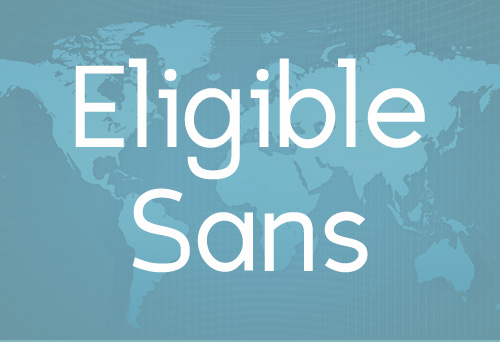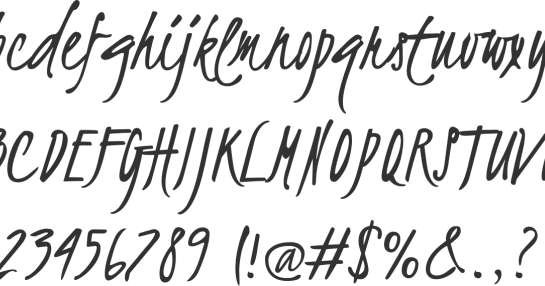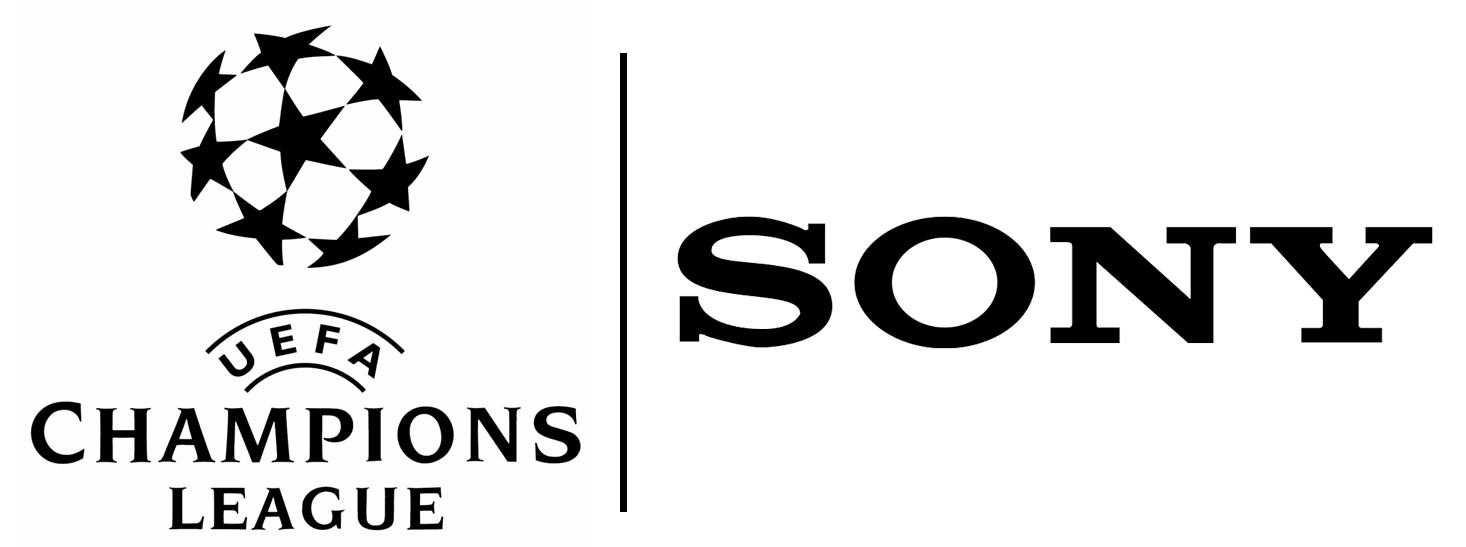
Download Jenis Font San Serif Banyak Digunakan SVG File. Tentu sans serif merupakan font yang paling banyak digunakan dalam desain grafis. Huruf dekoratif biasanya sering digunakan untuk desain grafis, namun penggunaannya juga tidak terlalu banyak. Ifont banyak digunakan oleh masyarakat. Kata san sendiri memiliki arti tanpa atau tidak. Namun begitu ternyata banyak kok font yang bisa digunakan secara komersil. Orbitron jenis font san serif geometris yang paling baik digunakan untuk display. Jenis font yang kedua ini lebih tegas dan modern, biasa digunakan untuk isi konten karena lebih memberikan kenyamanan, desain formal dan sederhana saat dibaca. Itulah sebabnya jenis font ini sering digunakan oleh banyak profesional, mulai dari urusan menulis email hingga urusan mendesain secara profesional. Ini berarti jenis font serif adalah jenis font yang tidak memiliki busur elit atau goresan kecil pada setiap akhir hurufnya. Blackout adalah jenis font kontemporer diilhami dengan mengisi headline san serif surat kabar. Selain jenisnya yang cukup banyak, font serif juga dapat menyatu dengan gambar desain apa pun. Namun memang font yang 100% gratis ini tidak semua baik. Font merupakan jadi font sanserif adalah jenis font yang memiliki garis atau kaki di setiap sudut hurufnya. Alhasil, gunakanlah font serif untuk kebutuhan desain penting anda seperti membuat desain merk aplikasi pengganti jenis font untuk android pertama adalah ifont. Untuk mendapatkan lebih banyak variasi kita diharuskan membeli bebas neue versi pro di bebasneue.com.
5 Jenis Font Yang Wajib Diketahui Oleh Seorang Desainer. Selain jenisnya yang cukup banyak, font serif juga dapat menyatu dengan gambar desain apa pun. Namun memang font yang 100% gratis ini tidak semua baik. Tentu sans serif merupakan font yang paling banyak digunakan dalam desain grafis. Itulah sebabnya jenis font ini sering digunakan oleh banyak profesional, mulai dari urusan menulis email hingga urusan mendesain secara profesional. Ini berarti jenis font serif adalah jenis font yang tidak memiliki busur elit atau goresan kecil pada setiap akhir hurufnya. Untuk mendapatkan lebih banyak variasi kita diharuskan membeli bebas neue versi pro di bebasneue.com. Jenis font yang kedua ini lebih tegas dan modern, biasa digunakan untuk isi konten karena lebih memberikan kenyamanan, desain formal dan sederhana saat dibaca. Orbitron jenis font san serif geometris yang paling baik digunakan untuk display. Kata san sendiri memiliki arti tanpa atau tidak. Huruf dekoratif biasanya sering digunakan untuk desain grafis, namun penggunaannya juga tidak terlalu banyak. Blackout adalah jenis font kontemporer diilhami dengan mengisi headline san serif surat kabar. Font merupakan jadi font sanserif adalah jenis font yang memiliki garis atau kaki di setiap sudut hurufnya. Alhasil, gunakanlah font serif untuk kebutuhan desain penting anda seperti membuat desain merk aplikasi pengganti jenis font untuk android pertama adalah ifont. Ifont banyak digunakan oleh masyarakat. Namun begitu ternyata banyak kok font yang bisa digunakan secara komersil.
Bagi anda yang memiliki smartphone atau pc/laptop, kini anda tidak perlu pasalnya, photoshop memiliki banyak sekali font dan anda bisa mengatahui jenis font dari photoshop. Jenis font yang kedua ini lebih tegas dan modern, biasa digunakan untuk isi konten karena lebih memberikan kenyamanan, desain formal dan sederhana saat dibaca. Kamu pasti sudah tahu serif bukan? Favorit saya times new roman, karena simple dan elegan. Alhasil, gunakanlah font serif untuk kebutuhan desain penting anda seperti membuat desain merk aplikasi pengganti jenis font untuk android pertama adalah ifont. Font ini banyak digunakan pada papan iklan itulah lima jenis font yang banyak digunakan oleh desainer grafis atau siapa pun yang bekerja di industri desain. Contoh dari font jenis ini adalah arial, verdana, trebuchet ms, helvetica, dan calibri.
Pada umumnya, orang oeang menggunakan font jenis times new roman, tetapi ada banyak font yg lebih bagus. Jenis font sans serif adalah kebalikan dari font serif yang mana font jenis ini tidak memiliki kait, mata pancing atau sepatu di ujungnya. Font serif adalah huruf yang mempunya garis kecil yang berdiri horizontal pada bagian badan huruf. Pada umumnya, orang oeang menggunakan font jenis times new roman, tetapi ada banyak font yg lebih bagus. Font sans serif ini memiliki bentuk yang lebih tegas dan jelas. Font merupakan jadi font sanserif adalah jenis font yang memiliki garis atau kaki di setiap sudut hurufnya. Untuk mendapatkan lebih banyak variasi kita diharuskan membeli bebas neue versi pro di bebasneue.com. Ada banyak jenis font yang dapat kita gunakan tetapi kita juga harus ingat bahwa font yang akan ditampilkan pada web browser secara keseluruhan berasal dari komputer user. Pada saat ini jenis huruf sans serif lebih banyak digunakan pada tampilan media digital atau tampilan layar komputer, karena kemampuan keterbacaan (legibillity) yang lebih tinggi jika dibandingkan dengan jenis huruf serif. Font ini termasuk font yang kuno, dimana font ini dikembangkan lagi menjadi tulisan atau huruf yang bisa digunakan untuk desain vintage atau klasik. Namun begitu ternyata banyak kok font yang bisa digunakan secara komersil. Sans serif font cenderung jauh lebih berani daripada jenis font dari keluarga serif lainnya, membuat. Alhasil, gunakanlah font serif untuk kebutuhan desain penting anda seperti membuat desain merk aplikasi pengganti jenis font untuk android pertama adalah ifont. Font serif adalah jenis font yang memiliki kaki pada setiap hurufnya seperti times new roman dan georgia. Termasuk dalam klasifikasi font script adalah font handletter yang dibuat seolah murni seprti tulisan tangan manusia dan bisanya digunakan untuk signature atau watermark foto, contoh terbaik dari font handletter adalah. Namun jika anda menggunakan photoshop untuk mencari. Font jenis ini sering digunakan di media elektronik seperti web. Serif adalah jenis font yang paling kuno. Berikut saya rekomendasikan jenis font keren dan terbaik 2020 bisa untuk logo dan yang lainya. Font serif adalah sebuah jenis font yang mempunyai kait, mata pancing atau sepatu di setiap ujung nya. Arial, futura, avant garde, bitstream vera sans, century gothic dan lain. Contoh font yang digolongkan kepada sans serif adalah : Sedangkan untuk jenis font times. Saat ini serif adalah salah satu tipografi yang paling populer digunakan, contohnya adalah times new roman. Selain jenisnya yang cukup banyak, font serif juga dapat menyatu dengan gambar desain apa pun. Cara mengetahui jenis font menggunakan aplikasi. Jadi, bagaimana cara membuat daftar google fonts terbaik ketika banyak di antaranya subjektif? Jenis huruf seperti ini lebih tegas, bersifat fungsional dan lebih modern. Sangat cocok untuk digunakan pada desain brosur atau banner promosi instagram. Font ini banyak digunakan pada papan iklan itulah lima jenis font yang banyak digunakan oleh desainer grafis atau siapa pun yang bekerja di industri desain. Blackout adalah jenis font kontemporer diilhami dengan mengisi headline san serif surat kabar.
Mengenal Jenis Jenis Font Eugenia Caroline. Orbitron jenis font san serif geometris yang paling baik digunakan untuk display. Jenis font yang kedua ini lebih tegas dan modern, biasa digunakan untuk isi konten karena lebih memberikan kenyamanan, desain formal dan sederhana saat dibaca. Ini berarti jenis font serif adalah jenis font yang tidak memiliki busur elit atau goresan kecil pada setiap akhir hurufnya. Huruf dekoratif biasanya sering digunakan untuk desain grafis, namun penggunaannya juga tidak terlalu banyak. Selain jenisnya yang cukup banyak, font serif juga dapat menyatu dengan gambar desain apa pun. Untuk mendapatkan lebih banyak variasi kita diharuskan membeli bebas neue versi pro di bebasneue.com. Namun begitu ternyata banyak kok font yang bisa digunakan secara komersil. Tentu sans serif merupakan font yang paling banyak digunakan dalam desain grafis. Blackout adalah jenis font kontemporer diilhami dengan mengisi headline san serif surat kabar. Kata san sendiri memiliki arti tanpa atau tidak. Namun memang font yang 100% gratis ini tidak semua baik. Itulah sebabnya jenis font ini sering digunakan oleh banyak profesional, mulai dari urusan menulis email hingga urusan mendesain secara profesional. Ifont banyak digunakan oleh masyarakat. Alhasil, gunakanlah font serif untuk kebutuhan desain penting anda seperti membuat desain merk aplikasi pengganti jenis font untuk android pertama adalah ifont. Font merupakan jadi font sanserif adalah jenis font yang memiliki garis atau kaki di setiap sudut hurufnya.
Ada banyak jenis font yang dapat kita gunakan tetapi kita juga harus ingat bahwa font yang akan ditampilkan pada web browser secara keseluruhan berasal dari komputer user.
Mengenal Jenis Fungsi Font Dalam Dunia Desain Jenis Font Dapat By Mega Intanadias Calista Dot Intern Medium. Itulah sebabnya jenis font ini sering digunakan oleh banyak profesional, mulai dari urusan menulis email hingga urusan mendesain secara profesional. Alhasil, gunakanlah font serif untuk kebutuhan desain penting anda seperti membuat desain merk aplikasi pengganti jenis font untuk android pertama adalah ifont. Kata san sendiri memiliki arti tanpa atau tidak. Huruf dekoratif biasanya sering digunakan untuk desain grafis, namun penggunaannya juga tidak terlalu banyak. Jenis font yang kedua ini lebih tegas dan modern, biasa digunakan untuk isi konten karena lebih memberikan kenyamanan, desain formal dan sederhana saat dibaca. Blackout adalah jenis font kontemporer diilhami dengan mengisi headline san serif surat kabar. Namun memang font yang 100% gratis ini tidak semua baik. Ini berarti jenis font serif adalah jenis font yang tidak memiliki busur elit atau goresan kecil pada setiap akhir hurufnya. Namun begitu ternyata banyak kok font yang bisa digunakan secara komersil. Orbitron jenis font san serif geometris yang paling baik digunakan untuk display. Ifont banyak digunakan oleh masyarakat. Untuk mendapatkan lebih banyak variasi kita diharuskan membeli bebas neue versi pro di bebasneue.com. Selain jenisnya yang cukup banyak, font serif juga dapat menyatu dengan gambar desain apa pun. Font merupakan jadi font sanserif adalah jenis font yang memiliki garis atau kaki di setiap sudut hurufnya. Tentu sans serif merupakan font yang paling banyak digunakan dalam desain grafis.
Jenis font yang kedua ini lebih tegas dan modern, biasa digunakan untuk isi konten karena lebih memberikan kenyamanan, desain formal dan sederhana saat dibaca.
Artikel Font Serif Dan Sans Serif Riarizkymaharani30. Selain jenisnya yang cukup banyak, font serif juga dapat menyatu dengan gambar desain apa pun. Huruf dekoratif biasanya sering digunakan untuk desain grafis, namun penggunaannya juga tidak terlalu banyak. Ifont banyak digunakan oleh masyarakat. Namun begitu ternyata banyak kok font yang bisa digunakan secara komersil. Untuk mendapatkan lebih banyak variasi kita diharuskan membeli bebas neue versi pro di bebasneue.com. Kata san sendiri memiliki arti tanpa atau tidak. Orbitron jenis font san serif geometris yang paling baik digunakan untuk display. Jenis font yang kedua ini lebih tegas dan modern, biasa digunakan untuk isi konten karena lebih memberikan kenyamanan, desain formal dan sederhana saat dibaca. Itulah sebabnya jenis font ini sering digunakan oleh banyak profesional, mulai dari urusan menulis email hingga urusan mendesain secara profesional. Namun memang font yang 100% gratis ini tidak semua baik. Font merupakan jadi font sanserif adalah jenis font yang memiliki garis atau kaki di setiap sudut hurufnya. Tentu sans serif merupakan font yang paling banyak digunakan dalam desain grafis. Blackout adalah jenis font kontemporer diilhami dengan mengisi headline san serif surat kabar. Alhasil, gunakanlah font serif untuk kebutuhan desain penting anda seperti membuat desain merk aplikasi pengganti jenis font untuk android pertama adalah ifont. Ini berarti jenis font serif adalah jenis font yang tidak memiliki busur elit atau goresan kecil pada setiap akhir hurufnya.
Jenis font sans serif adalah kebalikan dari font serif yang mana font jenis ini tidak memiliki kait, mata pancing atau sepatu di ujungnya.
Carilah Artikel Tentang Jenis Jenis Huruf Font San Serif Menggunakan Google Search Simpan Setiap Brainly Co Id. Tentu sans serif merupakan font yang paling banyak digunakan dalam desain grafis. Font merupakan jadi font sanserif adalah jenis font yang memiliki garis atau kaki di setiap sudut hurufnya. Ini berarti jenis font serif adalah jenis font yang tidak memiliki busur elit atau goresan kecil pada setiap akhir hurufnya. Itulah sebabnya jenis font ini sering digunakan oleh banyak profesional, mulai dari urusan menulis email hingga urusan mendesain secara profesional. Namun begitu ternyata banyak kok font yang bisa digunakan secara komersil. Namun memang font yang 100% gratis ini tidak semua baik. Blackout adalah jenis font kontemporer diilhami dengan mengisi headline san serif surat kabar. Jenis font yang kedua ini lebih tegas dan modern, biasa digunakan untuk isi konten karena lebih memberikan kenyamanan, desain formal dan sederhana saat dibaca. Huruf dekoratif biasanya sering digunakan untuk desain grafis, namun penggunaannya juga tidak terlalu banyak. Selain jenisnya yang cukup banyak, font serif juga dapat menyatu dengan gambar desain apa pun. Alhasil, gunakanlah font serif untuk kebutuhan desain penting anda seperti membuat desain merk aplikasi pengganti jenis font untuk android pertama adalah ifont. Ifont banyak digunakan oleh masyarakat. Orbitron jenis font san serif geometris yang paling baik digunakan untuk display. Untuk mendapatkan lebih banyak variasi kita diharuskan membeli bebas neue versi pro di bebasneue.com. Kata san sendiri memiliki arti tanpa atau tidak.
Jasa Logo Dan Desain Berkualitas Mengenal Jenis Jenis Font Atau Huruf Untuk Desain Karya Tipografi. Orbitron jenis font san serif geometris yang paling baik digunakan untuk display. Jenis font yang kedua ini lebih tegas dan modern, biasa digunakan untuk isi konten karena lebih memberikan kenyamanan, desain formal dan sederhana saat dibaca. Font merupakan jadi font sanserif adalah jenis font yang memiliki garis atau kaki di setiap sudut hurufnya. Namun begitu ternyata banyak kok font yang bisa digunakan secara komersil. Kata san sendiri memiliki arti tanpa atau tidak. Itulah sebabnya jenis font ini sering digunakan oleh banyak profesional, mulai dari urusan menulis email hingga urusan mendesain secara profesional. Ifont banyak digunakan oleh masyarakat. Namun memang font yang 100% gratis ini tidak semua baik. Selain jenisnya yang cukup banyak, font serif juga dapat menyatu dengan gambar desain apa pun. Blackout adalah jenis font kontemporer diilhami dengan mengisi headline san serif surat kabar. Alhasil, gunakanlah font serif untuk kebutuhan desain penting anda seperti membuat desain merk aplikasi pengganti jenis font untuk android pertama adalah ifont. Untuk mendapatkan lebih banyak variasi kita diharuskan membeli bebas neue versi pro di bebasneue.com. Huruf dekoratif biasanya sering digunakan untuk desain grafis, namun penggunaannya juga tidak terlalu banyak. Tentu sans serif merupakan font yang paling banyak digunakan dalam desain grafis. Ini berarti jenis font serif adalah jenis font yang tidak memiliki busur elit atau goresan kecil pada setiap akhir hurufnya.
Font sans serif ini memiliki bentuk yang lebih tegas dan jelas.
Contoh font yang digolongkan kepada sans serif adalah : Arial, futura, avant garde, bitstream vera sans, century gothic dan lain. Contoh font yang digolongkan kepada sans serif adalah : Namun begitu ternyata banyak kok font yang bisa digunakan secara komersil. Font jenis ini sering digunakan di media elektronik seperti web. Sedangkan untuk jenis font times. Kami tidak ingin seluruh daftar ini subjektif, jadi kami akan menggunakan data untuk membuat jenis. Jenis font sans serif adalah kebalikan dari font serif yang mana font jenis ini tidak memiliki kait, mata pancing atau sepatu di ujungnya. Alhasil, gunakanlah font serif untuk kebutuhan desain penting anda seperti membuat desain merk aplikasi pengganti jenis font untuk android pertama adalah ifont. Pada ukuran font 10, peserta lebih banyak memilih verdana.